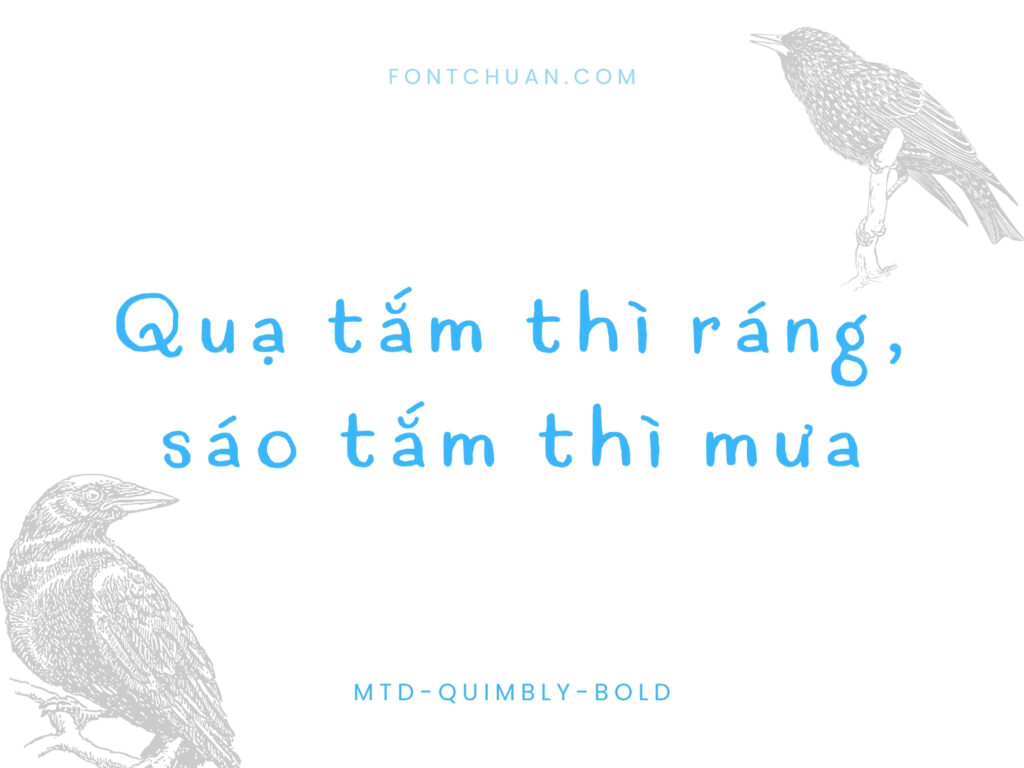
Font MTD Quimbly Việt Hóa
Tác giả Font: Magpie Paper Works
Font MTD Quimbly Bold là một phông chữ viết tay vui nhộn, được thiết kế bởi Magpie Paper Works và phát hành trên Creative Market. Font đã được Việt hóa bởi Mộc Hạ, hỗ trợ tiếng Việt và hơn 90 ngôn ngữ khác, giúp mở rộng khả năng ứng dụng trong các thiết kế đa ngôn ngữ. Đây là một trong những phông chữ được cộng đồng thiết kế đánh giá cao và ứng dụng trong nhiều dự án sáng tạo, đáp ứng nhu cầu đa dạng của người dùng.
MTD Quimbly Bold nổi bật với các đường nét viết tay tự nhiên, mang đến cảm giác thân thiện và gần gũi. Font rất phù hợp cho các thiết kế logo, tiêu đề, bao bì sản phẩm, thiệp mời và các ấn phẩm đòi hỏi sự sáng tạo và cá nhân hóa. Các ngành nghề phù hợp bao gồm quảng cáo, giáo dục, công nghệ, thiệp cưới và ảnh cưới. Font này cũng lý tưởng cho các sự kiện như Tết, Giáng sinh, Valentine và các lễ hội khác.